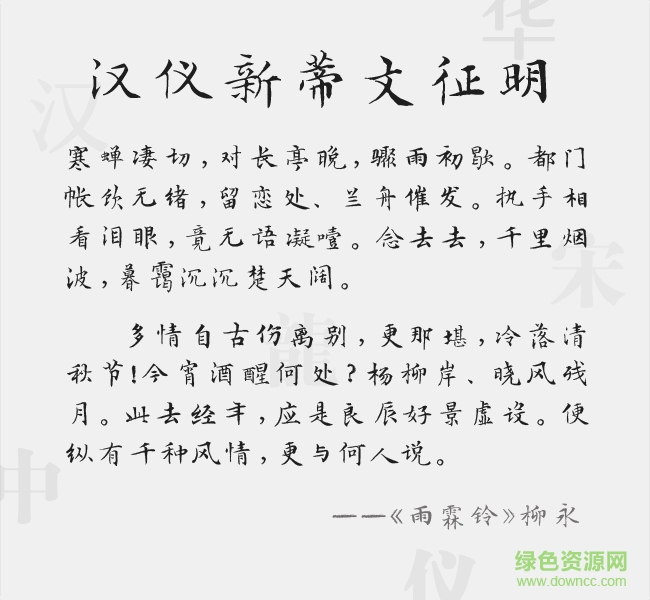
漢儀新蒂文征明體字體是一款極具個性的漢儀字體,該字體棱角分明,整體效果十分大氣,能夠滿足產(chǎn)品包裝、廣告宣傳、出版印刷、商標用字、商業(yè)網(wǎng)站、影視影像視頻、書籍出版印刷等,有需要的朋友可以免費下載收藏。
漢儀新蒂文征明體是漢儀字體庫中的個性字體,字體擁有非常精致的字型,有喜歡的朋友就趕快來綠色資源網(wǎng)下載使用吧!